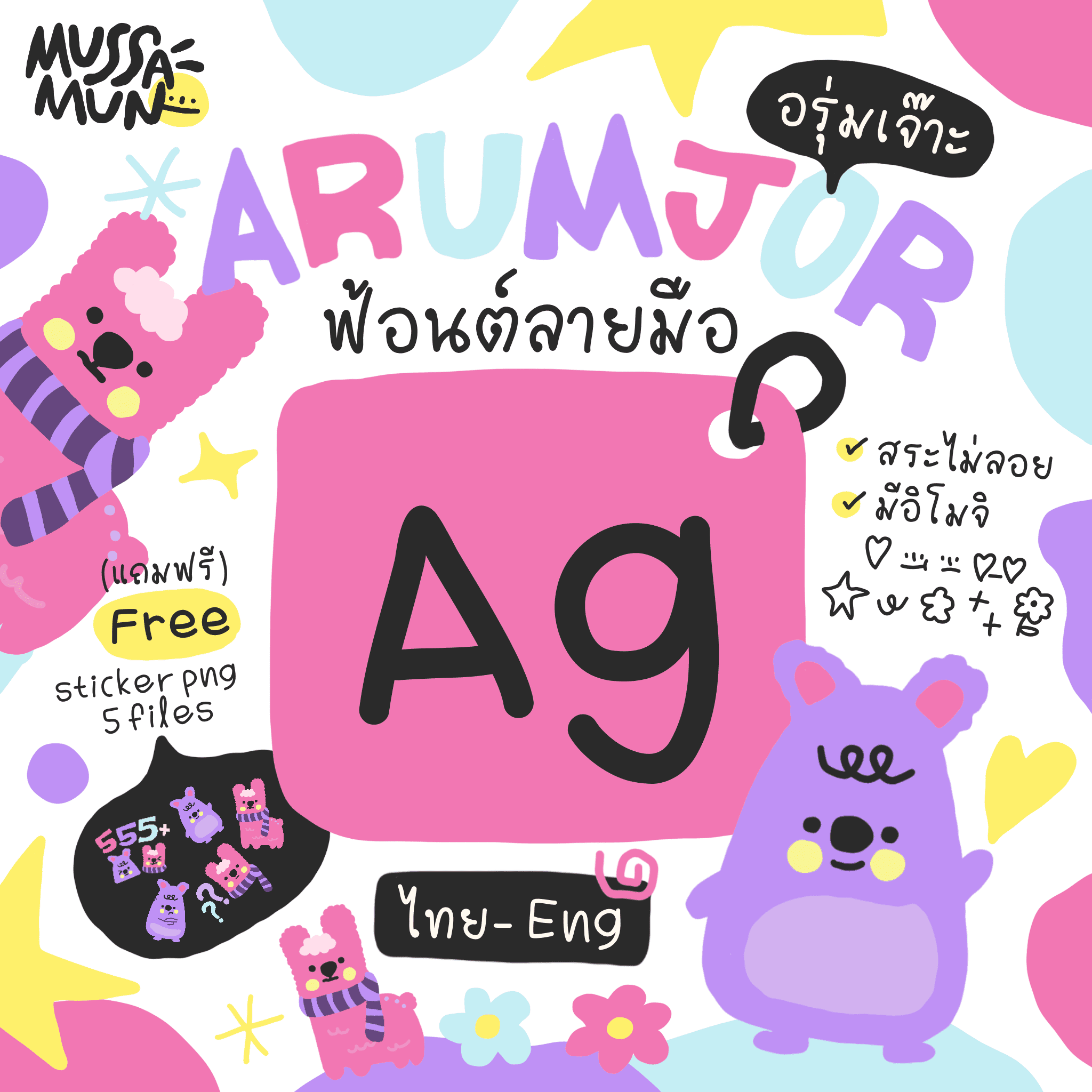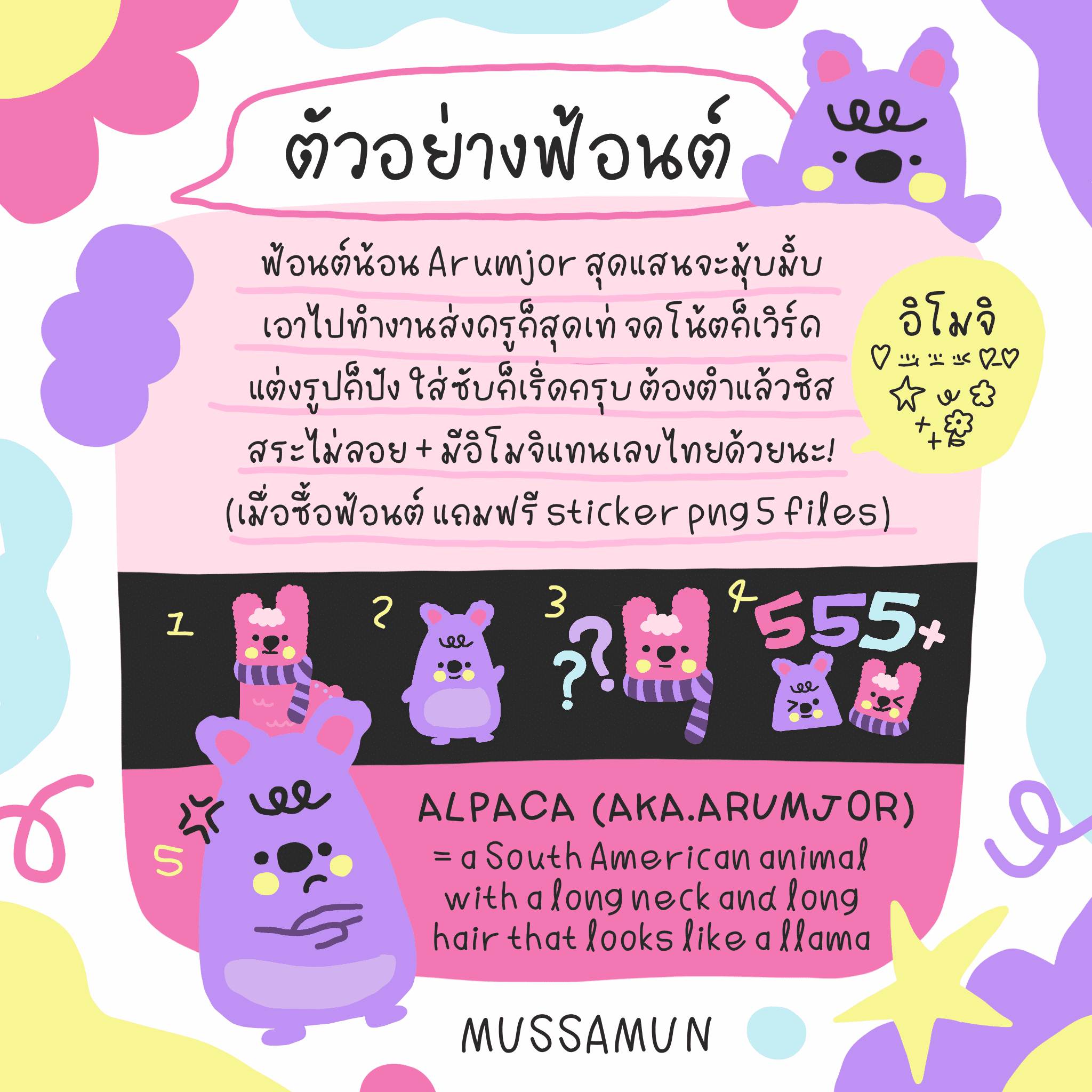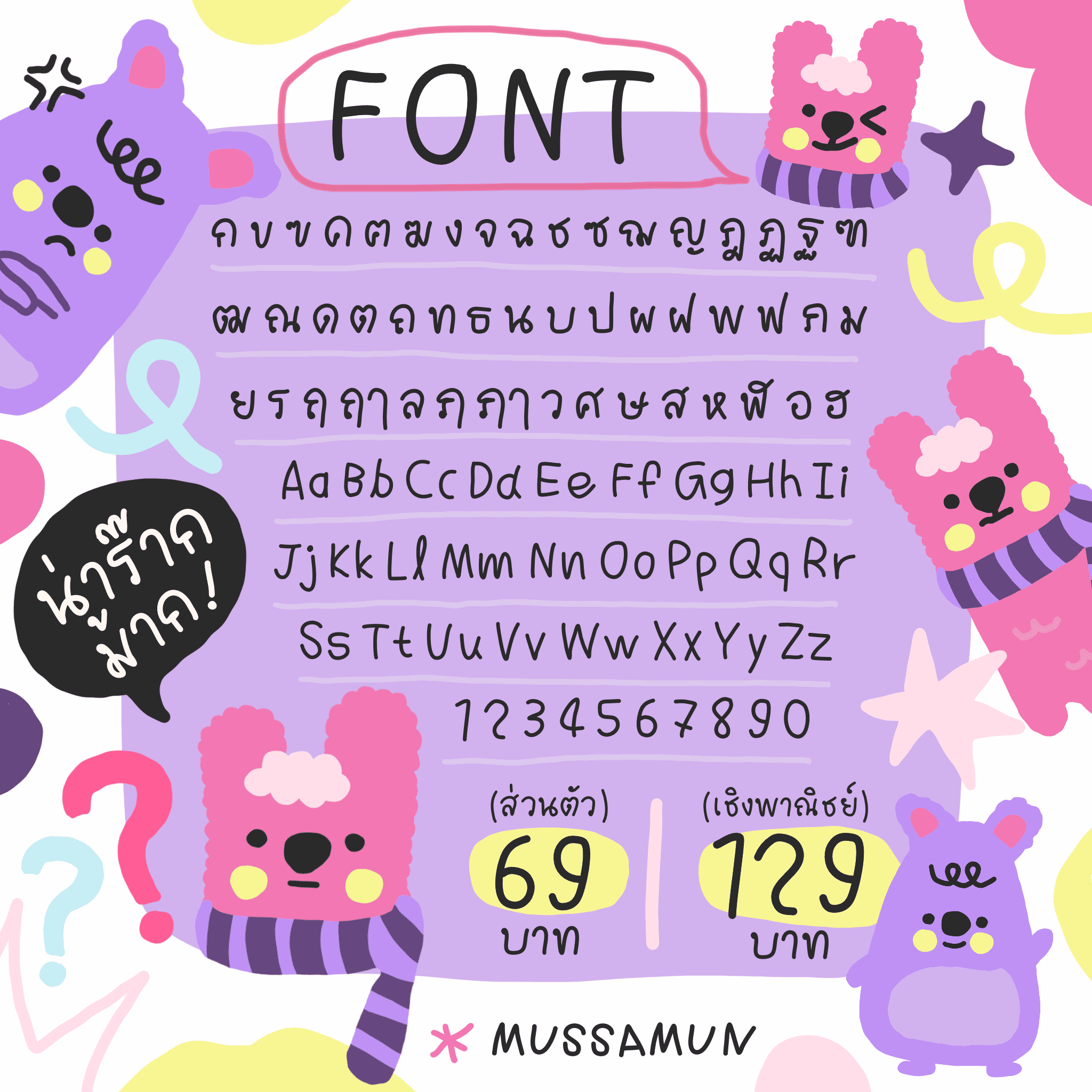
MUSSAMUN | FONT (Arumjor)
ฟ้อนต์ Arumjor🦙 สุดแสนจะน่ารัก หัวดำอ่านง่าย จะจดโน้ต, ทำงานส่งครู , แต่งรูป , ใส่ซับ หรืออื่นๆก็น่ารักไปหมด นอกจากความน่ารัก มีอิโมจิแทนที่เลขไทย* 🖇ยังแถมฟรี! sticker png 5 files เอาไปตกแต่งได้เลยน้า